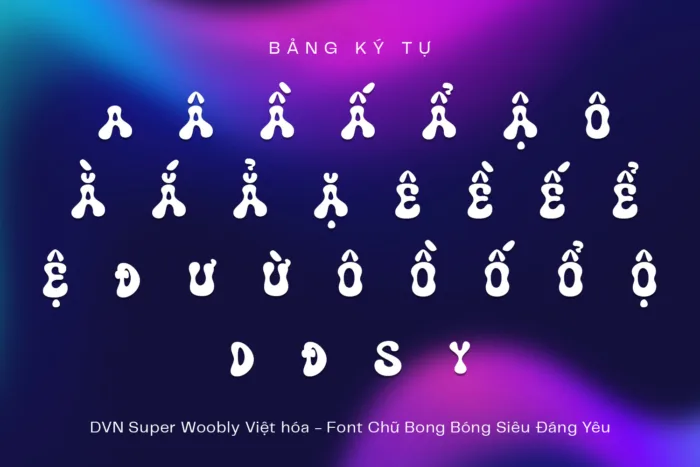
DVN Super Woobly Việt hóa – Font Chữ Bong Bóng Siêu Đáng Yêu
DVN Super Woobly là một kiểu chữ hiển thị mang phong cách bong bóng dẻo siêu đáng yêu và vui nhộn. Các ký tự được bo tròn, phồng lên như kẹo dẻo, kết hợp với hiệu ứng sáng bóng tạo cảm giác lấp lánh và sống động như đang bật ra khỏi trang giấy. Font đặc biệt phù hợp với các thiết kế dành cho trẻ em, tiêu đề vui nhộn, poster sự kiện, sticker, hoặc các dự án sáng tạo mang tính giải trí.
Bản Việt hóa giữ nguyên tinh thần “woobly” độc đáo của font gốc, đồng thời bổ sung đầy đủ dấu tiếng Việt để bạn dễ dàng sử dụng trong các thiết kế của bạn.